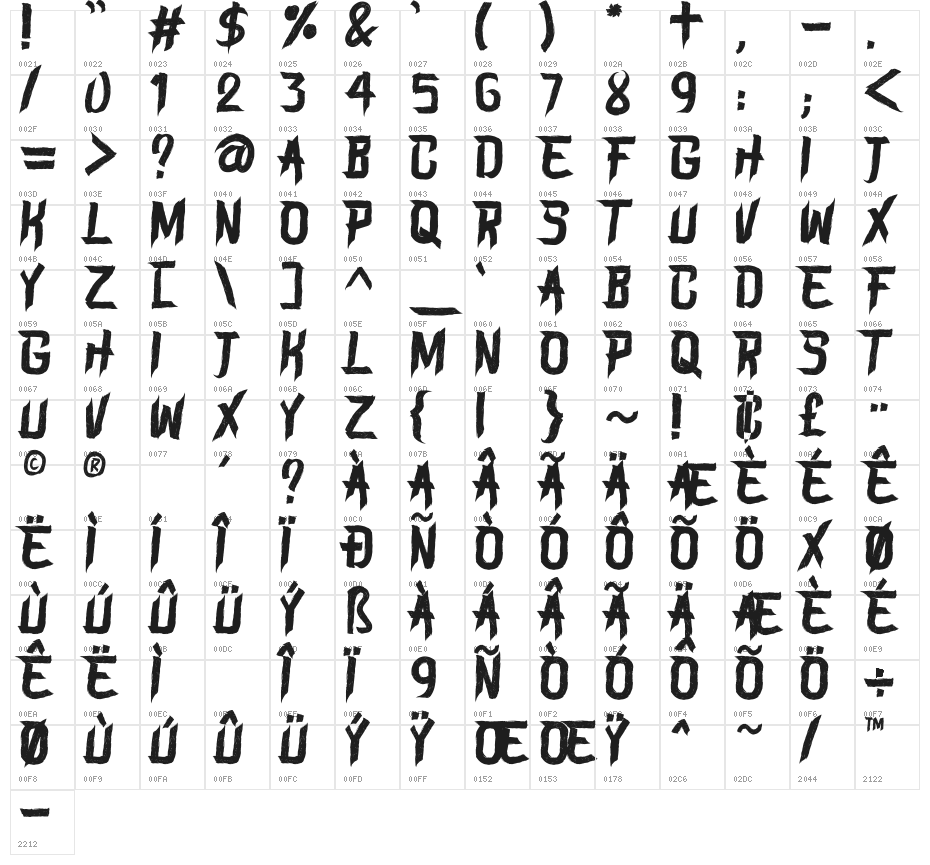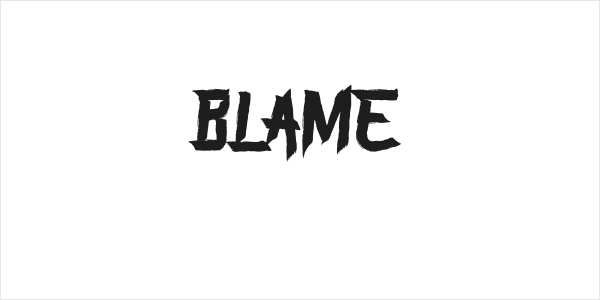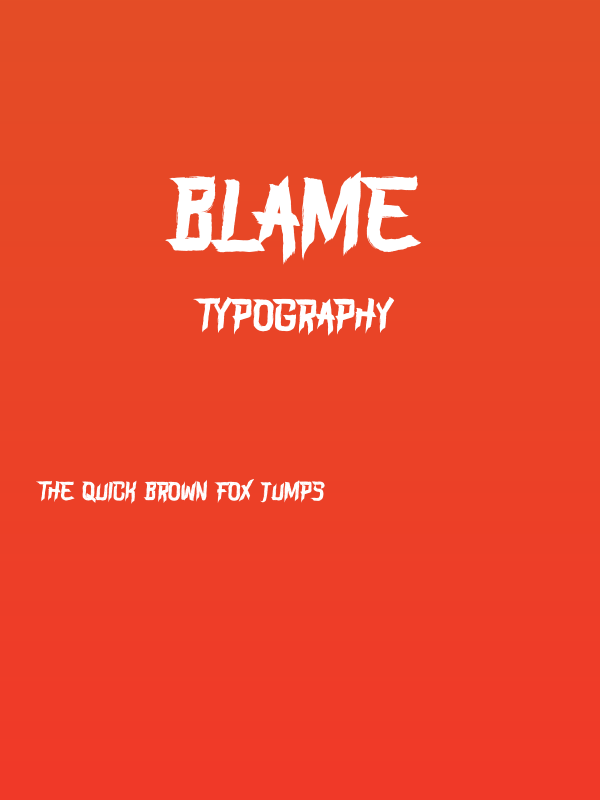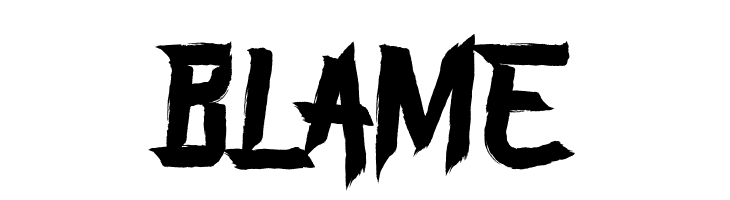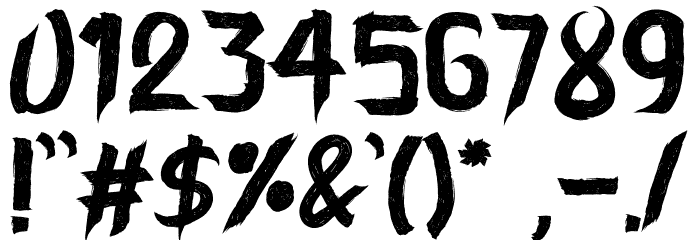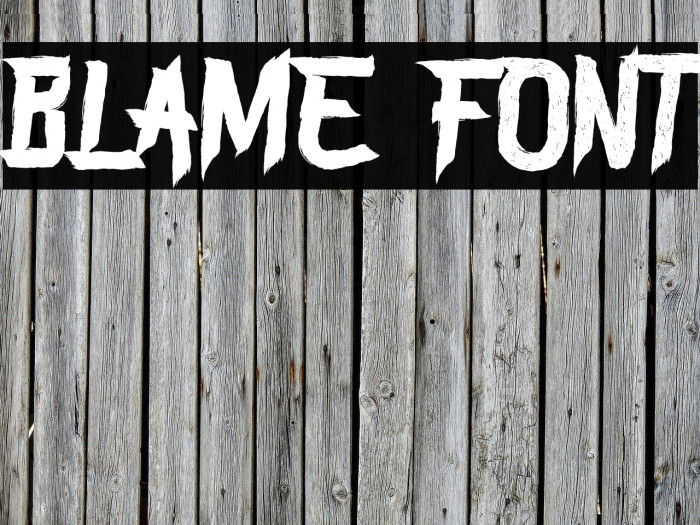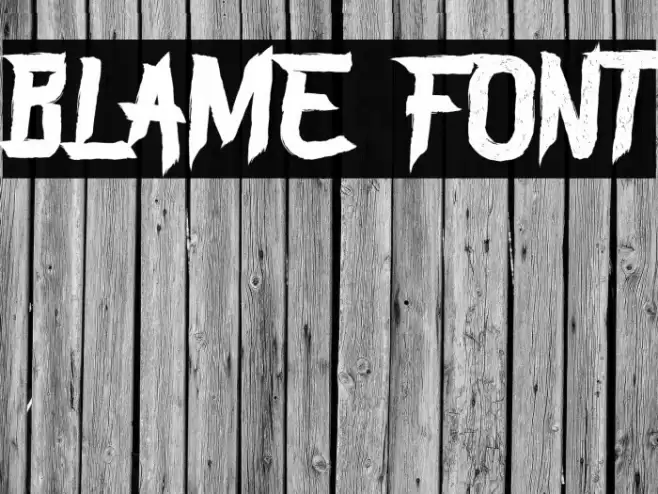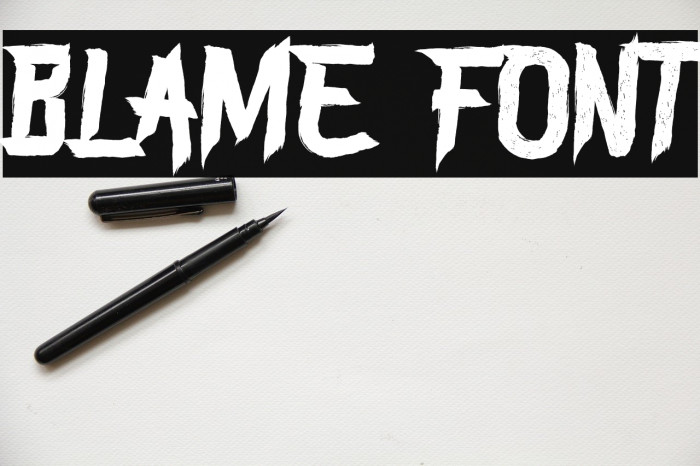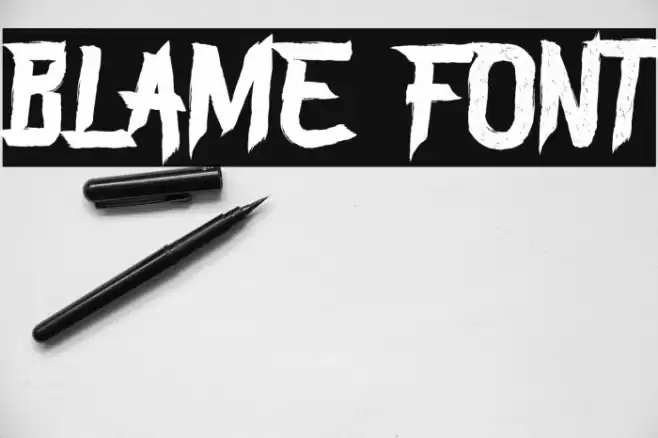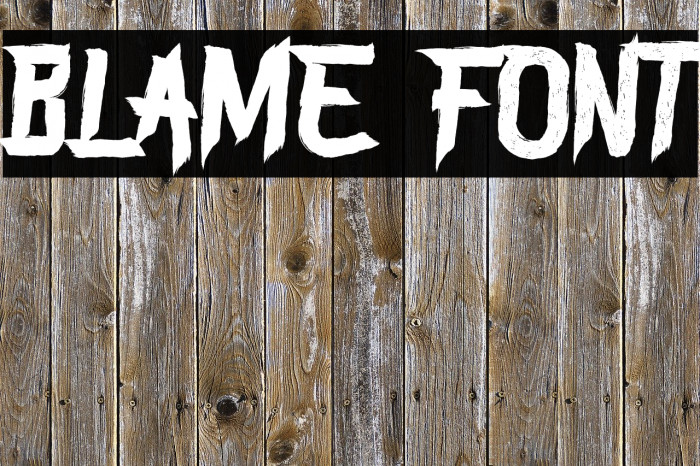
BLAME Font
✎ Messy
| श्रेणियाँ | Messy |
| समग्र शैली | Decorative |
| उपयोग का मामला | Headlines, Logos |
| सुझाए गए प्रोजेक्ट | Ideal for music album covers, posters, branding for extreme sports, or any project needing a bold, edgy look. |